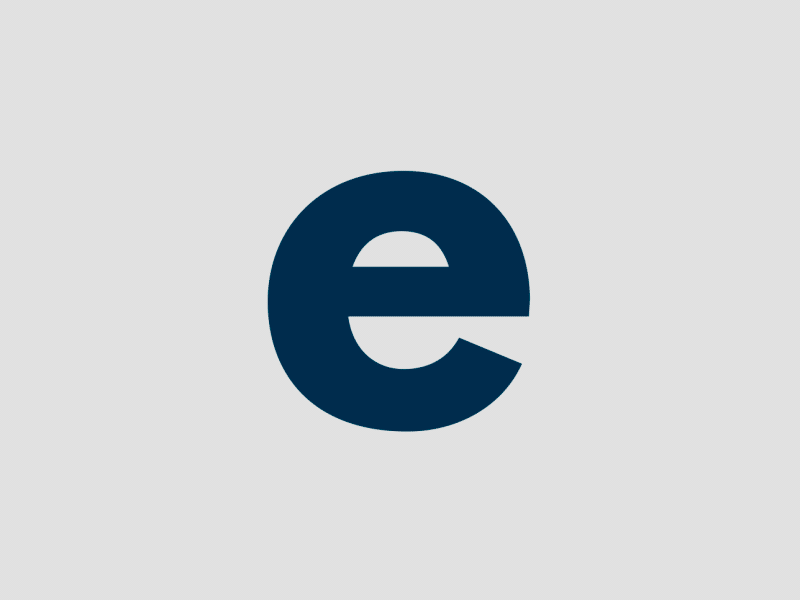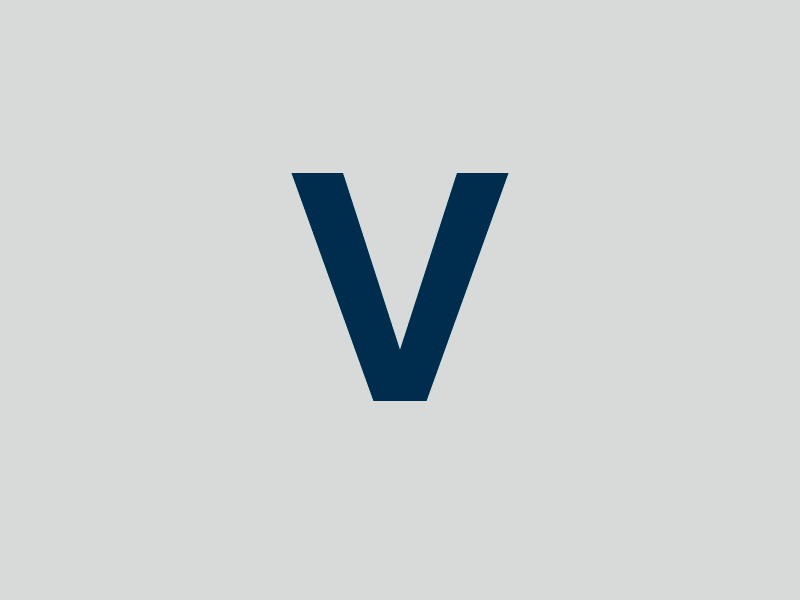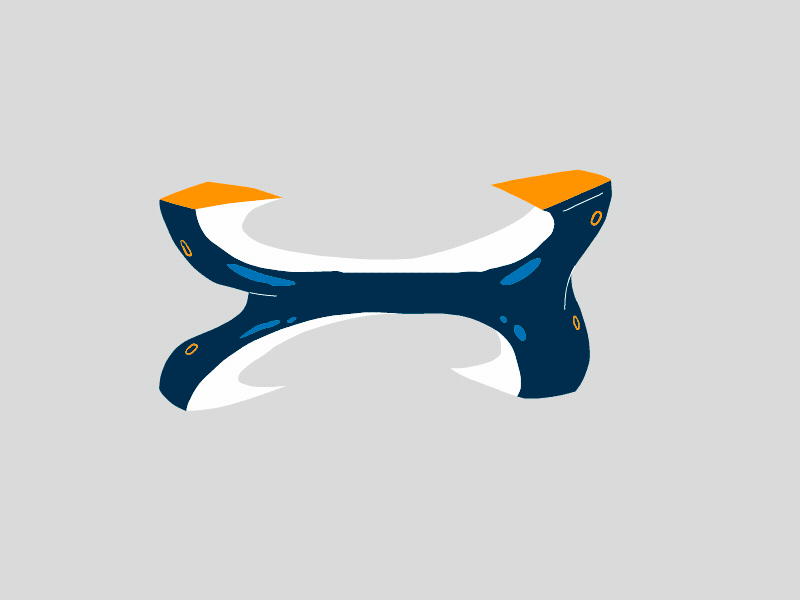
Animography, a medio camino entre animación y tipografía
El diseño, como campo creativo, es flexible y siempre está abierto a la experimentación y la colaboración.
Jeroen Krielaars, de la fundidora neerlandesa Animography lo sabe bien y ha creado la tipografía Mobilo Animated, a medio camino entre la animación y la tipografía. Se trata no sólo de una fundición de diferentes disciplinas, sino una colaboración de profesionales de todos los rincones del planeta; que, además, se puede descargar de manera gratuita.
La tipografía corre a cargo de Alfredo Marco Pradil, quien se encargó de diseñar los ocho pesos de Mobilo disponibles en la web de Animography. En la animación, sin embargo, han colaborado 236 profesionales del motion graphic.
A cada motion grapher se le asignó un glifo de la misma tipografía y se le encargó que llevase a cabo una animación con total liberta. Las únicas limitaciones eran: utilizar la tipografía Mobilo, no usar más de cuatro colores, debían acotarse a un espacio de 500x600px y no debía durar más de un segundo dividido en 25 frames. Esto permitió que, a pesar de que cada uno de los glifos proviene de un artistas y una parte del mundo completamente diferente, existe una uniformidad en el proyecto.
Existen más tipografías dinámicas, la propia Animography ya creo Franchise de una manera similar a la que ha utilizado para dar vida a Mobilo; pero esta vez el proyecto tiene más del doble de colaboradores y el boom de las tipografías cinéticas está en su punto de ebullición.
Algunos de los animadores involucrados en el proyecto son Zenzuke, Pablo Lozano (Golden Wolf), Rafa Galeano. En el vídeo a continuación puedes ver todas las animaciones y descubrir a sus autores.